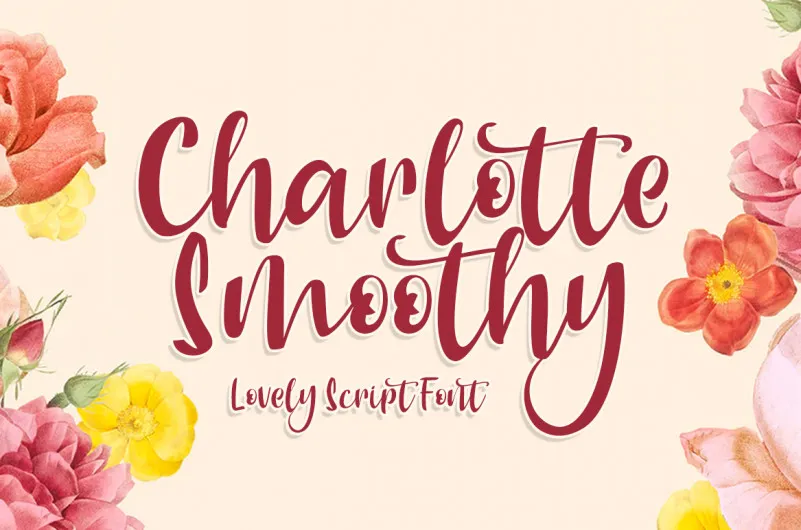
Charlotte Smoothy Script Font – Download Grátis
A Charlotte Smoothy Script Font é uma elegante e impecável tipografia script, com letras atraentes e traços extravagantes que te deixarão adorando seu encanto romântico. Escreva ou desenhe como quereriam ver um poema ser escrita – fluido, amoroso e cheio de vida, esta fonte é perfeita para aqueles designers apaixonados por texturas delicadas e gráficos de alta qualidade. Ideal para aplicar em design editorial, cartões personalizados ou qualquer projeto que precise de uma pitada de romantismo moderno e sofisticado. Seja o criador do próximo hit digital com essa fonte de primeira linha. A agniardi nos presenteia com a Charlotte Smoothy Script Font, um tesouro para qualquer designer gráfico que deseja trazer um toque autêntico e único à sua produção visual. Não hesite em explorar e experimentar o encanto desta fonte, pois ela certamente não vai decepcioná-lo.